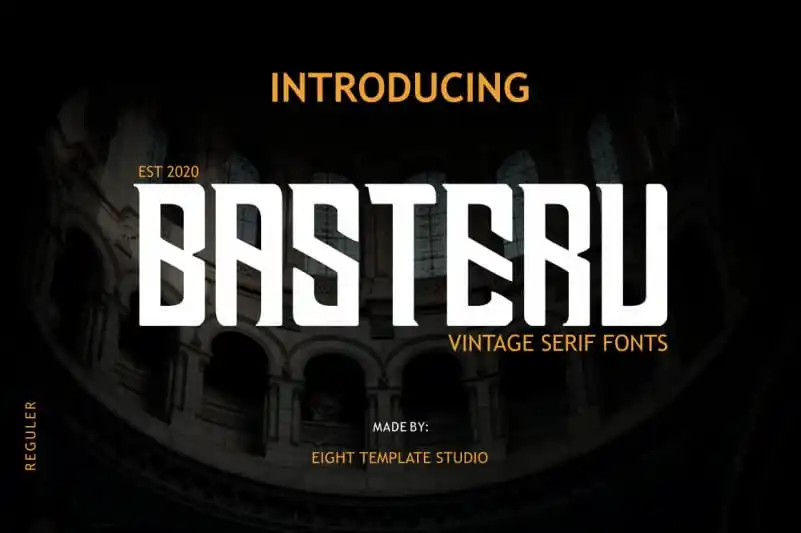
Basteru Vintage Serif Font – Download Grátis
Basteru Vintage Serif Font é uma escolha perfeita para designers que buscam uma fonte de display com estilo vintage e elegante. Esta fonte apresenta fortes linhas e um tom poderoso, ideal para criar designs memoráveis e logos duradouros. Com Basteru Vintage Serif Font, você pode transformar qualquer projeto em algo excepcionalmente belo e único. Este tipo vem já com textura aplicada, fornecendo o toque de luxo que seus projetos merecem. Esse é um excelente exemplo de uma fonte serif de designer vintage, perfeitamente adaptado para ambientes de display. Kumsstudio, a equipe criativa por trás desta fonte, oferece esta opção sofisticada e elegante para quem busca uma fonte que se destaca no meio do design gráfico contemporâneo. Seja para um site, um livro impresso ou até mesmo uma camiseta personalizada, Basteru Vintage Serif Font é uma escolha inteligente para aqueles buscando um toque de luxo e sofisticação em seus projetos.